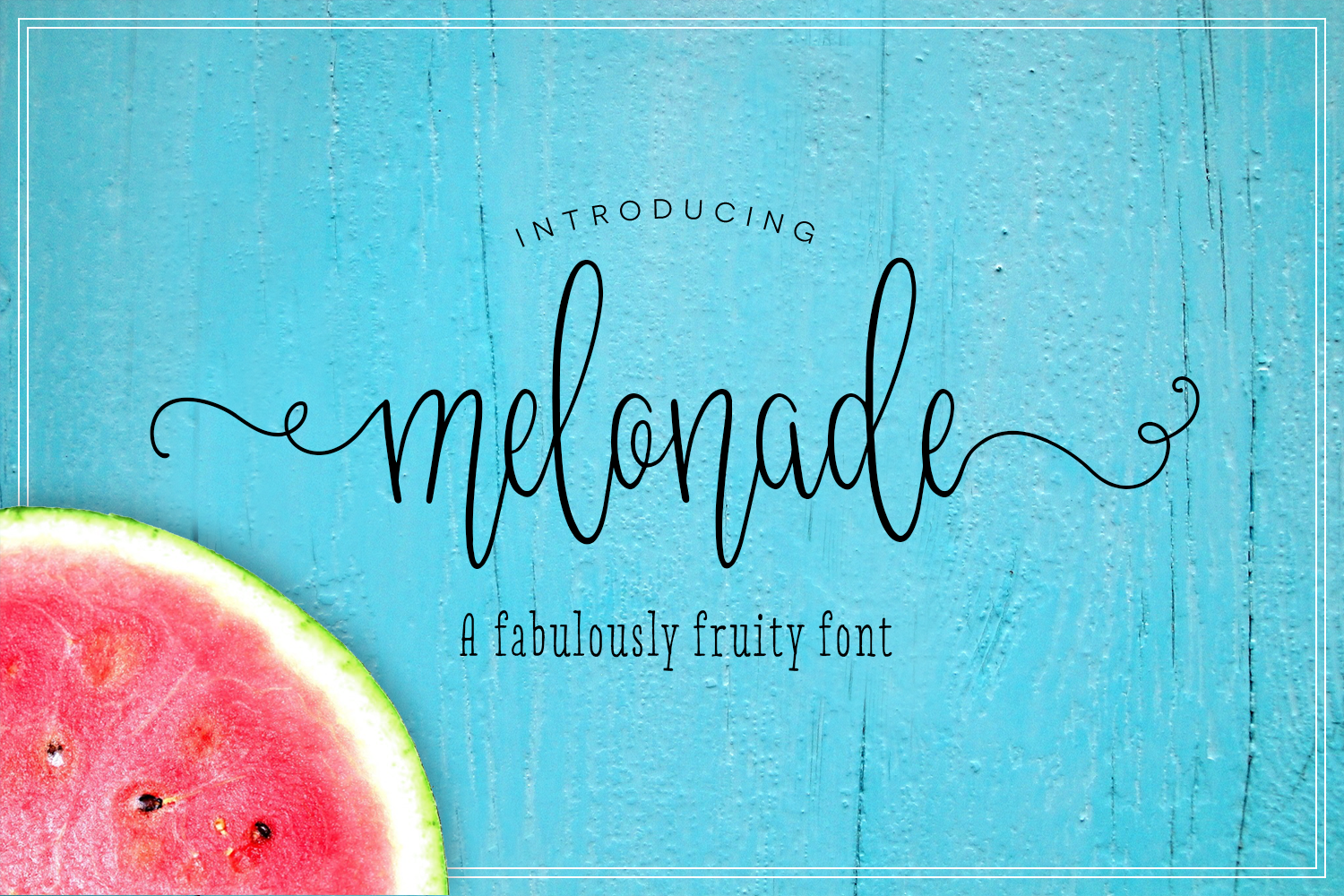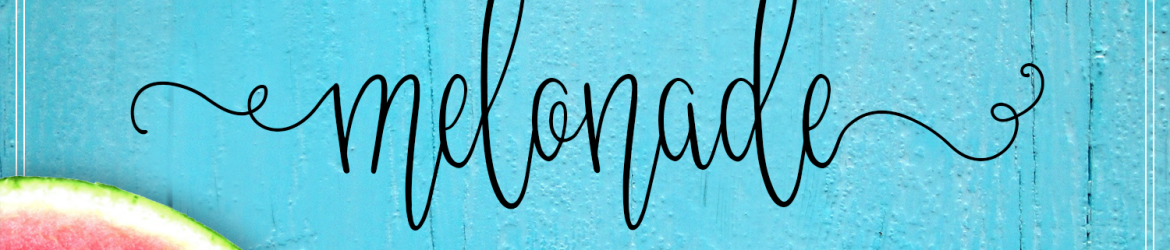
Introduzimos a nova ‘Melonade’, uma fonte de script escrita à mão que se destaca por sua elegância e fluididade. Desenvolvida pela Kirsten Louise Design, Melonade é uma fonte com traços altos perfeitamente projetada para trazer um toque de criatividade e personalização a qualquer projeto. Seu formato permite adicionar tanto swashes da esquerda quanto da direita ao conjunto padrão de letras, o que oferece infinitas possibilidades de criação. Através de sua versatilidade, Melonade se destaca como uma escolha perfeita para diversos tipos de trabalhos, desde postagens nas redes sociais e gráficos publicitários até identidades digitais, embalagens de produtos e design de casamentos. Suas linhas fluidas e personalizáveis tornam-a ideal para expressar o sentimento autêntico das suas mensagens, seja em um convite especial ou uma etiqueta de embalagem exclusiva. Melonade é a escolha perfeita para aqueles que procuram adicionar um toque único à sua identidade visual.